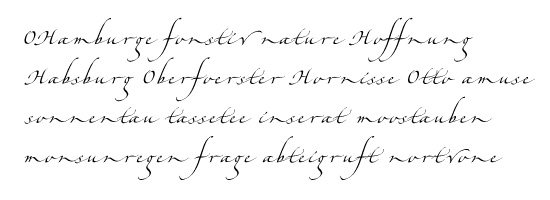
Hamada (Linotype)
Die Hamada™ von Linotype ist eine kraftvolle Schreibschrift und die
digitale Umsetzung des Werkes von Gaynor Goffe, einer englischen
Kalligraphin. Akira Kobayashi, künstlerischer Leiter bei Linotype, griff
direkt auf die Handschrift von Gaynor Goffe zurück, um die Buchstaben
zu digitalisieren. Die daraus entstandene Hamada hat eine Ausstrahlung
wie mit Federkiel auf Papier geschrieben, mit Tintenrändern an den
Konturen und Bewegung zwischen den Kurven, Buchstaben und Linien.
Daraus entsteht ein wunderschönes Schriftbild, besonders in grossen
Graden. Dank den Möglichkeiten des OpenType-Formats entsteht
bei Hamada der Eindruck echter Kalligraphie – ein Effekt ganz ähnlich
wie bei der berühmten Zapfino.